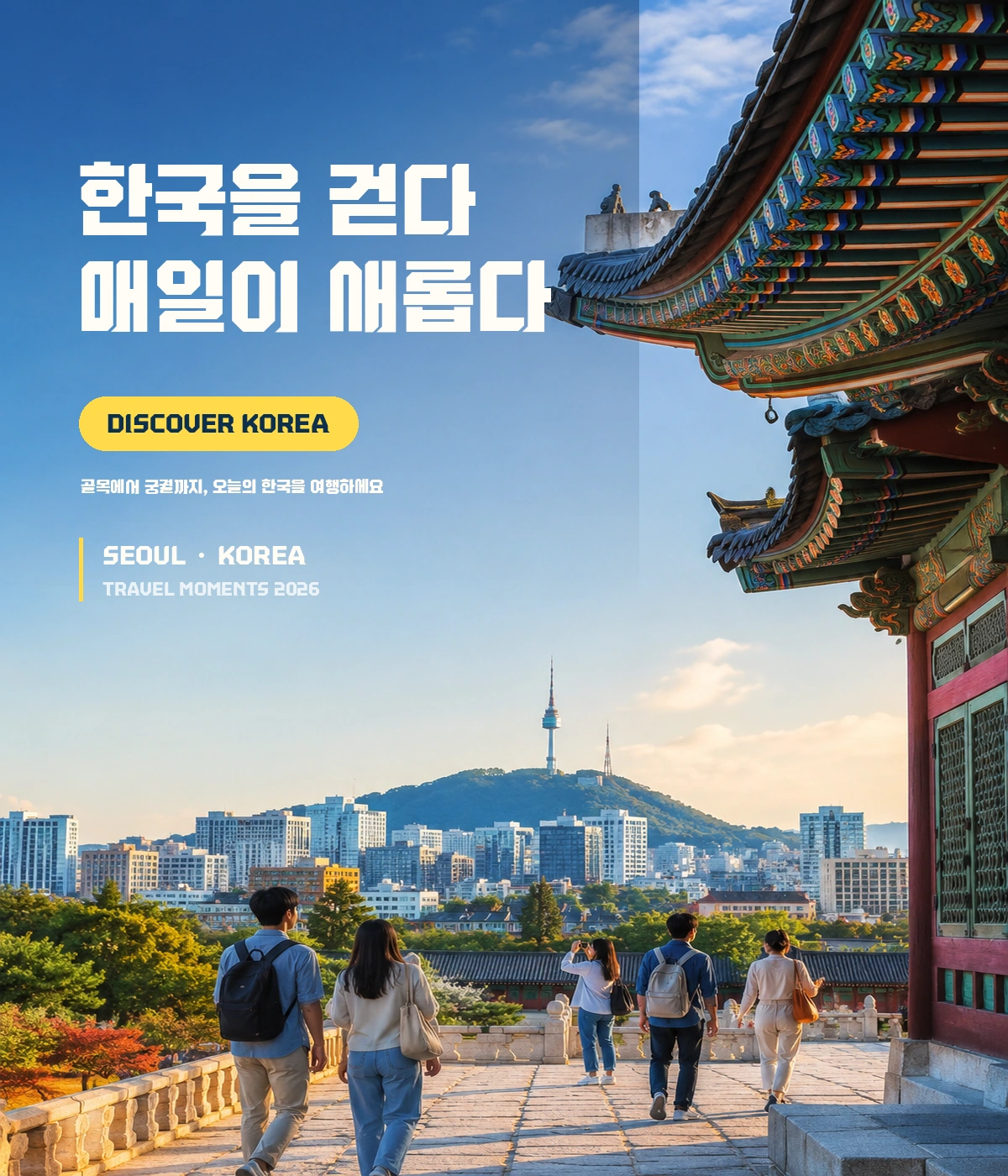
하이커체 — 한국관광공사에서 배포하는 무료 폰트입니다. 복합 문화공간 하이커 그라운드의 로고를 한글로 다시 그린, 시선을 끄는 제목용 서체
한국관광공사가 배포하는 서체입니다. 이름 때문에 등산이나 걷기여행길을 떠올리기 쉬운데, **그쪽이 아니라 하이커 그라운드라는 복합 문화공간**에서 왔습니다. 서울 청계천의 하이커 그라운드와 인천공항의 하이커 스테이션이 그것이고, 이름은 한국을 찾은 여행자에게 건네는 인사인 Hi from Korea에서 시작됐습니다.
어떻게 만들었는지 공사가 적어 두었습니다. 하이커가 사람들과 소통하는 또 하나의 목소리이기에, 공간과 웹사이트, SNS 콘텐츠 전반의 톤앤매너를 살펴보고 하이커만의 감성을 글자 속에도 담아낼 수 있도록 방향을 잡았다는 것입니다. 조형의 출발점은 영문 로고입니다. HiKR 영문 로고에서 시작해 한글 구조에 맞게 재해석했다고 밝혔습니다.
특징 네 가지도 밝혀 두었습니다. 아이덴티티의 핵심 조형인 **45도 사선**을 구조에 반영해 생동감을 더했고, 로고타입의 캐릭터를 적극적으로 반영했으며, 사용성을 고려한 웨이트 설계로 강한 시각적 임팩트를 주었고, 로고의 조형 규칙을 유지하면서도 한글 인지에 문제가 없도록 균형 있게 설계했다는 것입니다.
숨은 재미가 하나 있습니다. **글자만 있는 폰트가 아니라 하이커를 상징하는 눈알 캐릭터가 이모지로 들어 있고**, 타이핑하다 보면 몰래 등장하는 캐릭터도 있다고 합니다. 문자표를 열어 찾아보세요.